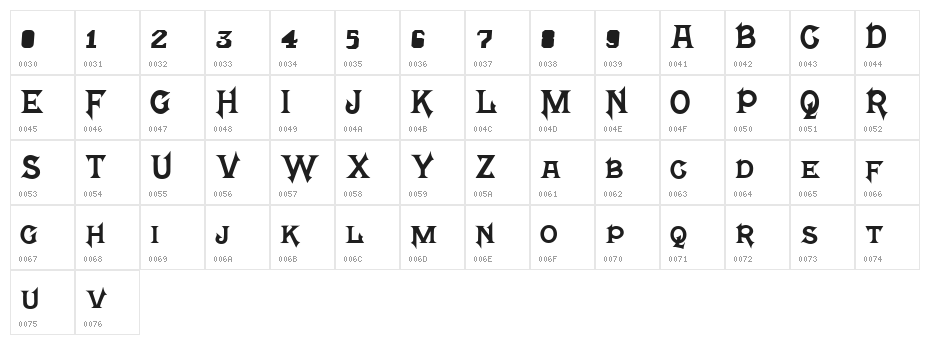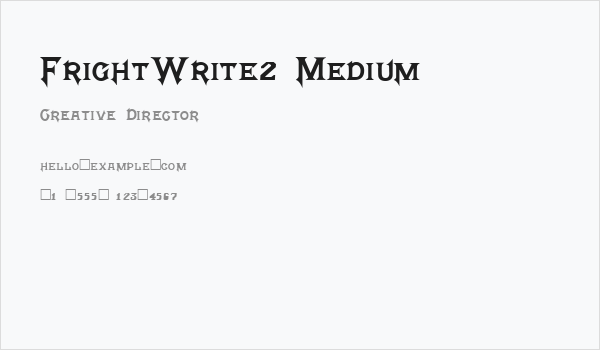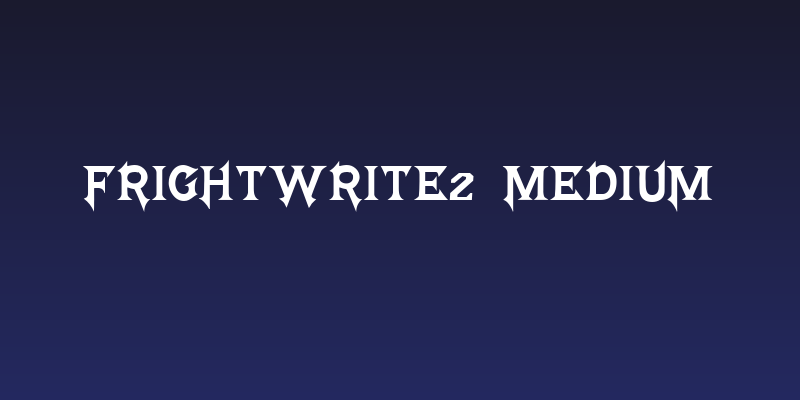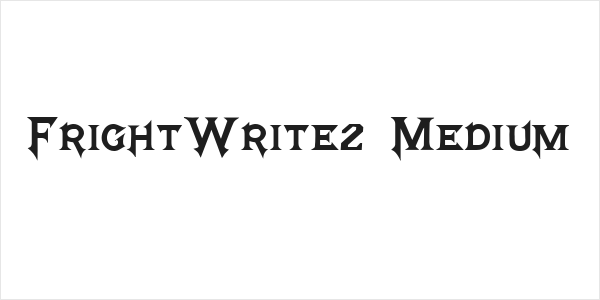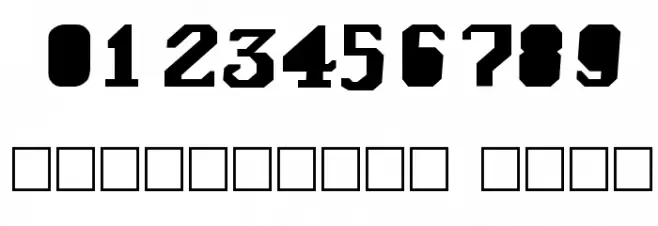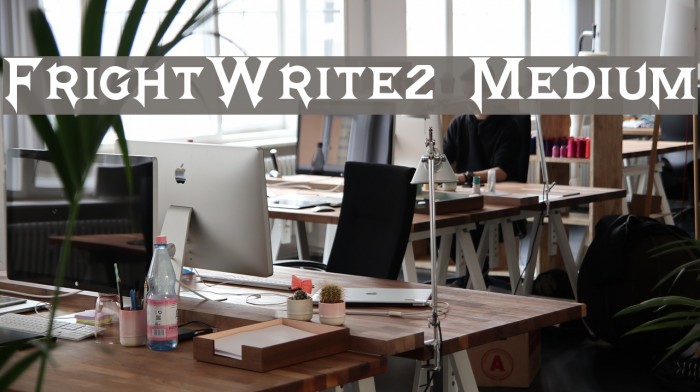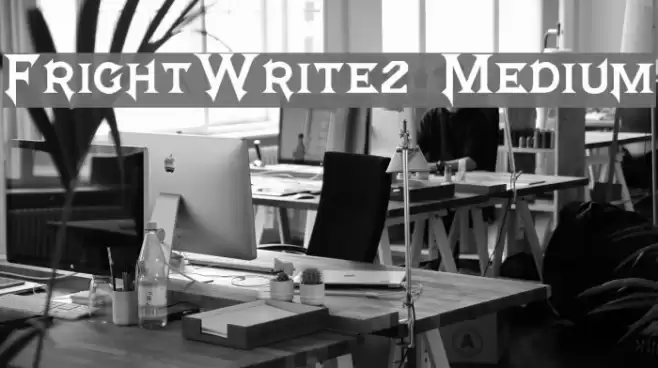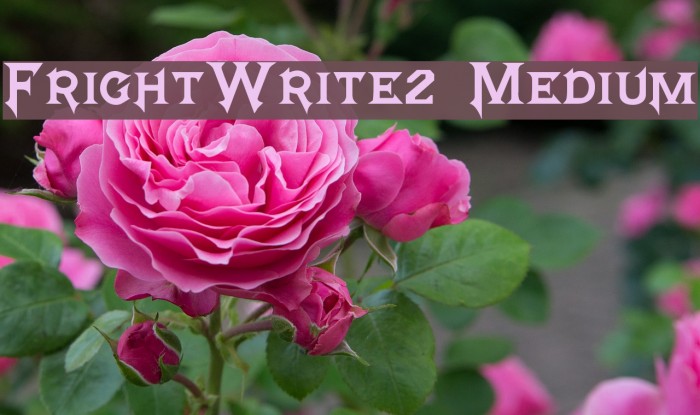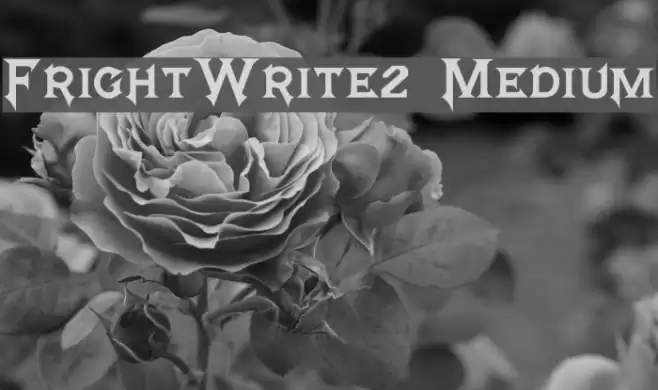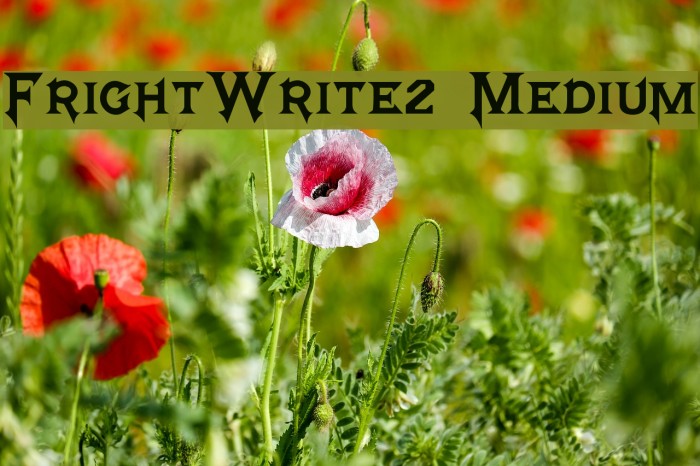
FrightWrite2 Medium Font
| Style général | Gothic, Decorative |
| Cas d'utilisation | Headlines, Posters, Branding |
| Projets proposés | Ideal for use in horror-themed posters, edgy branding, or any design requiring a bold, attention-grabbing font. |